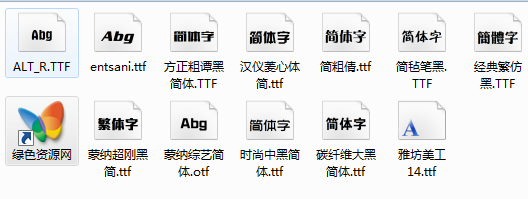
十二款電視綜藝節(jié)目廣告字體打包分享了常用的綜藝節(jié)目logo設(shè)計(jì)字體,很多電視綜藝都是用到這些字體,比如大家熟悉的爸爸去哪兒,中國(guó)好聲音等,看著那些華麗的字體你是否也想試一試,下載這些字體,發(fā)揮你的創(chuàng)造力也可以設(shè)計(jì)出非常好看的喲。
《爸爸去哪兒》Logo用的什么字體?《中國(guó)好聲音》Logo用的什么字體?《中國(guó)最強(qiáng)音》Logo用的什么字體?......其實(shí),基本上只要有一定知名度的電視綜藝類(lèi)節(jié)目所使用的形象字體都是或多或少經(jīng)過(guò)重新設(shè)計(jì)的。不過(guò)他們也是經(jīng)過(guò)這些基礎(chǔ)字體重新設(shè)計(jì)的,下面介紹的就是這些綜藝節(jié)目常用字體
漢儀菱心體簡(jiǎn)
碳纖維大黑簡(jiǎn)體
a_AlternaRg
Enter Sansman
方正粗譚黑簡(jiǎn)體
時(shí)尚中黑簡(jiǎn)體
蒙納綜藝簡(jiǎn)體
蒙納超剛黑簡(jiǎn)
簡(jiǎn)氈筆黑
簡(jiǎn)粗倩
經(jīng)典繁仿黑
雅坊美工14